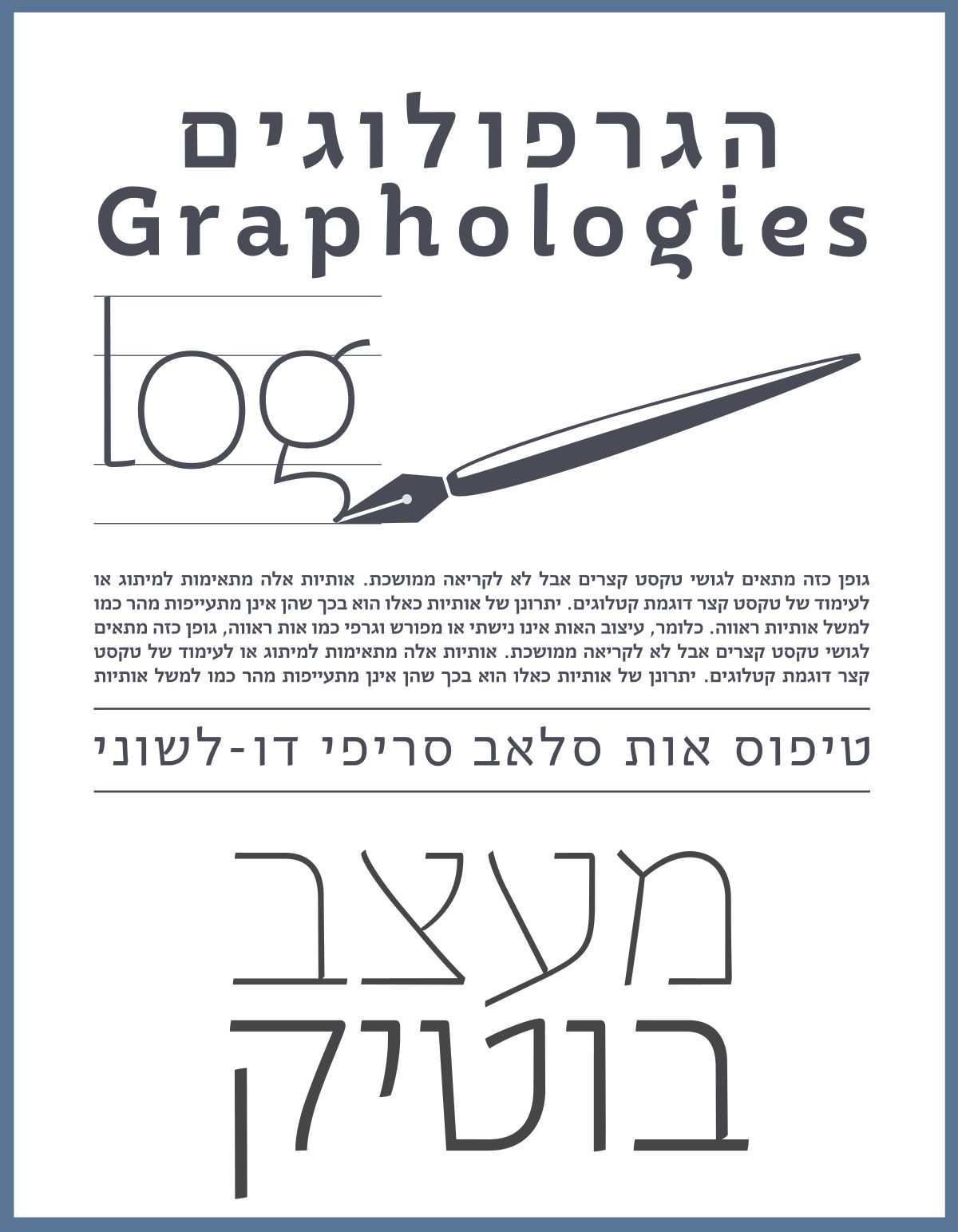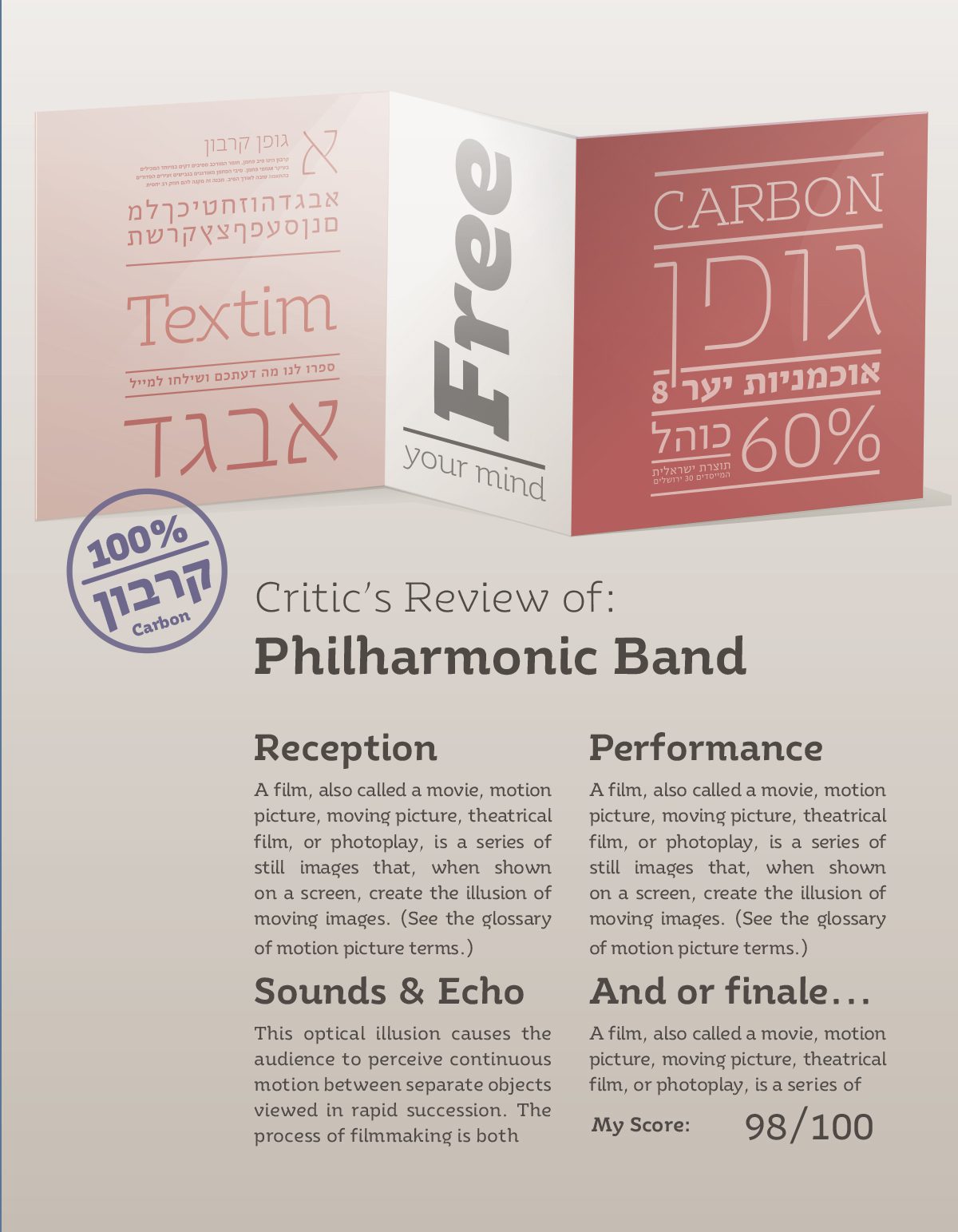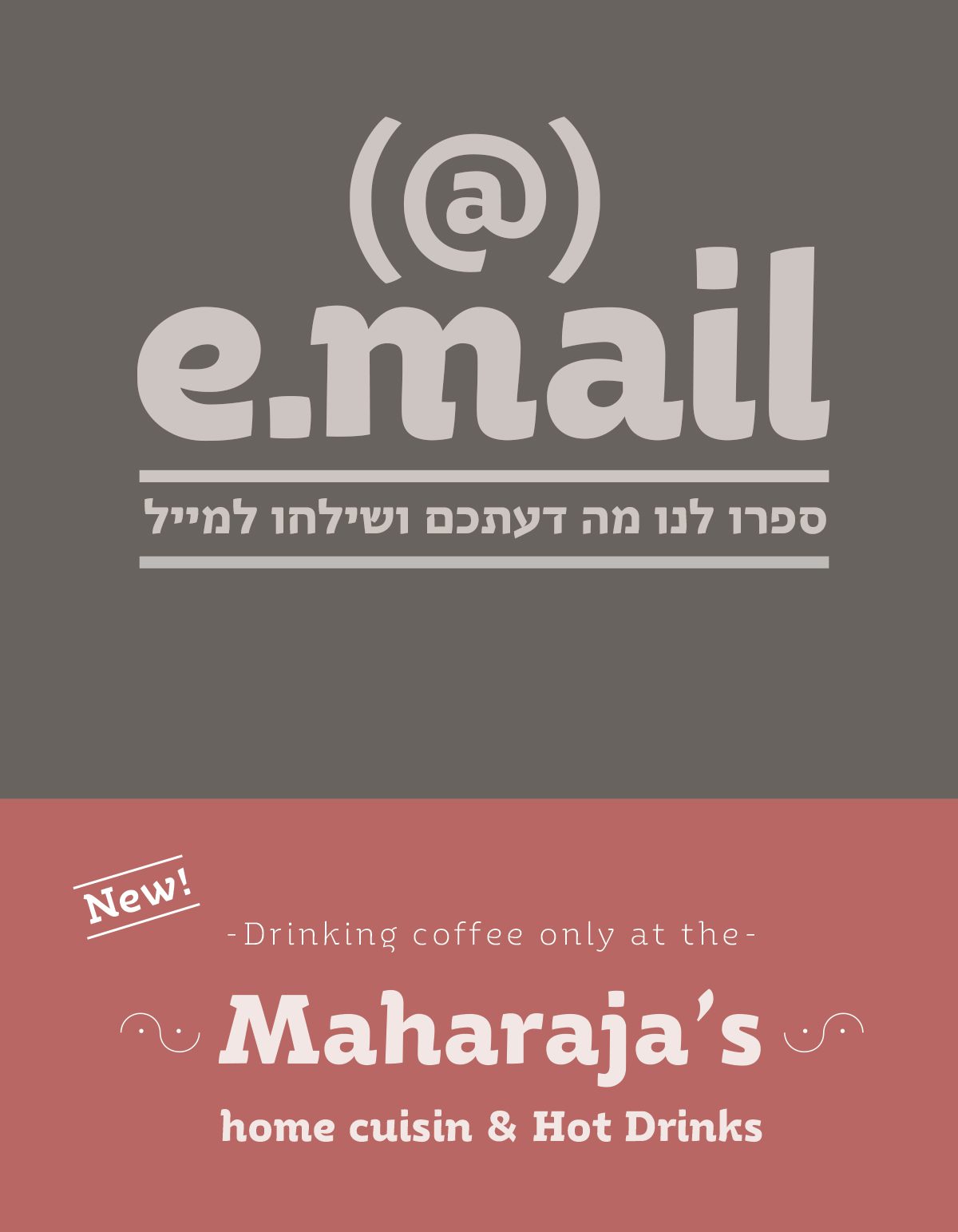
אטמוספירה אשר מלאה בחמצן דו-פחמני Atmosphere is full of Carbon & dioxide
אקספרמנטלי
טיפוגרפי חזק דו-לשוני Typography Eng/Heb
שקטות 38
האלפבית העברי מאכלס בתוכו מטען תרבותי רב-ערך. מטען זה מתבטא באופן בו התכונות לובשות צורה כאותיות המתקיימות יחד בהרמוניה. אות היא אמנם היחידה הקטנה והבסיסית ביותר במערך הטיפוגרפי השלם, אבל למרות מימדיה לאות יש השפעה משמעותית על המבנה החזותי של המילה, המשפט ולבסוף על תצורת הטקסט המעומד בשלמותו. פיתוח טיפוס אות, הינו תהליך של התגבשות הצורות וחיפוש אחר איזון בין התכונה של המבנה הכללי לבין התכונה הייחודית של כל אחת מהאותיות. אות היא אמנם היחידה הקטנה והבסיסית ביותר שבכל המערך הטיפוגרפי אבל למרות מימדיה לאות יש השפעה משמעותית על כל המבנה החזותי של המילה, המשפט ולבסוף גם על תצורת הטקסט המעומד בשלמותו. תפיסת העיצוב בפונטביט היא חופש וחדוות יצירה עם הערכה רבה למקור האלפבית העברי שמאכלס בתוכו מטען תרבותי רב-ערך. מטען זה מתבטא באופן בו התכונות לובשות צורה כאותיות המתקיימות יחד בהרמוניה. אות היא אמנם היחידה הקטנה והבסיסית ביותר במערך הטיפוגרפי השלם, אבל למרות מימדיה לאות יש השפעה משמעותית על המבנה החזותי של המילה, המשפט ולבסוף על תצורת הטקסט המעומד בשלמותו. פיתוח טיפוס אות, הינו תהליך של התגבשות הצורות וחיפוש אחר איזון בין התכונה של המבנה הכללי לבין התכונה הייחודית של כל אחת מהאותיות תפיסת העיצוב בפונטביט היא חופש וחדוות יצירה עם הערכה רבה למקור האלפבית העברי שמאכלס בתוכו מטען תרבותי רב-ערך. מטען זה מתבטא באופן בו התכונות לובשות צורה כאותיות המתקיימות יחד בהרמוניה. אות היא אמנם היחידה הקטנה והבסיסית ביותר במערך הטיפוגרפי השלם, אבל למרות מימדיה לאות יש השפעה משמעותית על המבנה החזותי של המילה, המשפט ולבסוף על תצורת הטקסט המעומד בשלמותו. פיתוח טיפוס אות, הינו תהליך של התגבשות הצורות וחיפוש אחר איזון בין התכונה של המבנה הכללי לבין התכונה הייחודית של כל אחת מהאותיות.
תפיסת העיצוב בפונטביט היא חופש וחדוות יצירה עם הערכה רבה למקור האלפבית העברי שמאכלס בתוכו מטען תרבותי רב-ערך. מטען זה מתבטא באופן בו התכונות לובשות צורה כאותיות המתקיימות יחד בהרמוניה. אות היא אמנם היחידה הקטנה והבסיסית ביותר במערך הטיפוגרפי השלם, אבל למרות מימדיה לאות יש השפעה משמעותית על המבנה החזותי של המילה, המשפט ולבסוף על תצורת הטקסט המעומד בשלמותו. פיתוח טיפוס אות, הינו תהליך של התגבשות הצורות וחיפוש אחר איזון בין התכונה של המבנה הכללי לבין התכונה הייחודית של כל אחת מהאותיות. אות היא אמנם היחידה הקטנה והבסיסית ביותר שבכל המערך הטיפוגרפי אבל למרות מימדיה לאות יש השפעה משמעותית על כל המבנה החזותי של המילה, המשפט ולבסוף גם על תצורת הטקסט המעומד בשלמותו. תפיסת העיצוב בפונטביט היא חופש וחדוות יצירה עם הערכה רבה למקור האלפבית העברי שמאכלס בתוכו מטען תרבותי רב-ערך. מטען זה מתבטא באופן בו התכונות לובשות צורה כאותיות המתקיימות יחד בהרמוניה. אות היא אמנם היחידה הקטנה והבסיסית ביותר במערך הטיפוגרפי השלם, אבל למרות מימדיה לאות יש השפעה משמעותית על המבנה החזותי של המילה, המשפט ולבסוף על תצורת הטקסט המעומד בשלמותו. פיתוח טיפוס אות, הינו תהליך של התגבשות הצורות וחיפוש אחר איזון בין התכונה של המבנה הכללי לבין התכונה הייחודית של כל אחת מהאותיות תפיסת העיצוב בפונטביט היא חופש וחדוות יצירה עם הערכה רבה למקור האלפבית העברי שמאכלס בתוכו מטען תרבותי רב-ערך. מטען זה מתבטא באופן בו התכונות לובשות צורה כאותיות המתקיימות יחד בהרמוניה. אות היא אמנם היחידה הקטנה והבסיסית ביותר במערך הטיפוגרפי השלם, אבל למרות מימדיה לאות יש השפעה משמעותית על המבנה החזותי של המילה, המשפט ולבסוף על תצורת הטקסט המעומד בשלמותו. פיתוח טיפוס אות, הינו תהליך של התגבשות הצורות וחיפוש אחר איזון בין התכונה של המבנה הכללי לבין התכונה הייחודית של כל אחת מהאותיות.
אות היא אמנם היחידה הקטנה והבסיסית ביותר שבכל המערך הטיפוגרפי אבל למרות מימדיה לאות יש השפעה משמעותית על כל המבנה החזותי של המילה, המשפט ולבסוף גם על תצורת הטקסט המעומד בשלמותו. תפיסת העיצוב בפונטביט היא חופש וחדוות יצירה עם הערכה רבה למקור האלפבית העברי שמאכלס בתוכו מטען תרבותי רב-ערך. מטען זה מתבטא באופן בו התכונות לובשות צורה כאותיות המתקיימות יחד בהרמוניה. אות היא אמנם היחידה הקטנה והבסיסית ביותר במערך הטיפוגרפי השלם, אבל למרות מימדיה לאות יש השפעה משמעותית על המבנה החזותי של המילה, המשפט ולבסוף על תצורת הטקסט המעומד בשלמותו. פיתוח טיפוס אות, הינו תהליך של התגבשות הצורות וחיפוש אחר איזון בין התכונה של המבנה הכללי לבין התכונה הייחודית של כל אחת מהאותיות תפיסת העיצוב בפונטביט היא חופש וחדוות יצירה עם הערכה רבה למקור האלפבית העברי שמאכלס בתוכו מטען תרבותי רב-ערך. מטען זה מתבטא באופן בו התכונות לובשות צורה כאותיות המתקיימות יחד בהרמוניה. אות היא אמנם היחידה הקטנה והבסיסית ביותר במערך הטיפוגרפי השלם, אבל למרות מימדיה לאות יש השפעה משמעותית על המבנה החזותי של המילה, המשפט ולבסוף על תצורת הטקסט המעומד בשלמותו. פיתוח טיפוס אות, הינו תהליך של התגבשות הצורות וחיפוש אחר איזון בין התכונה של המבנה הכללי לבין התכונה הייחודית של כל אחת מהאותיות.